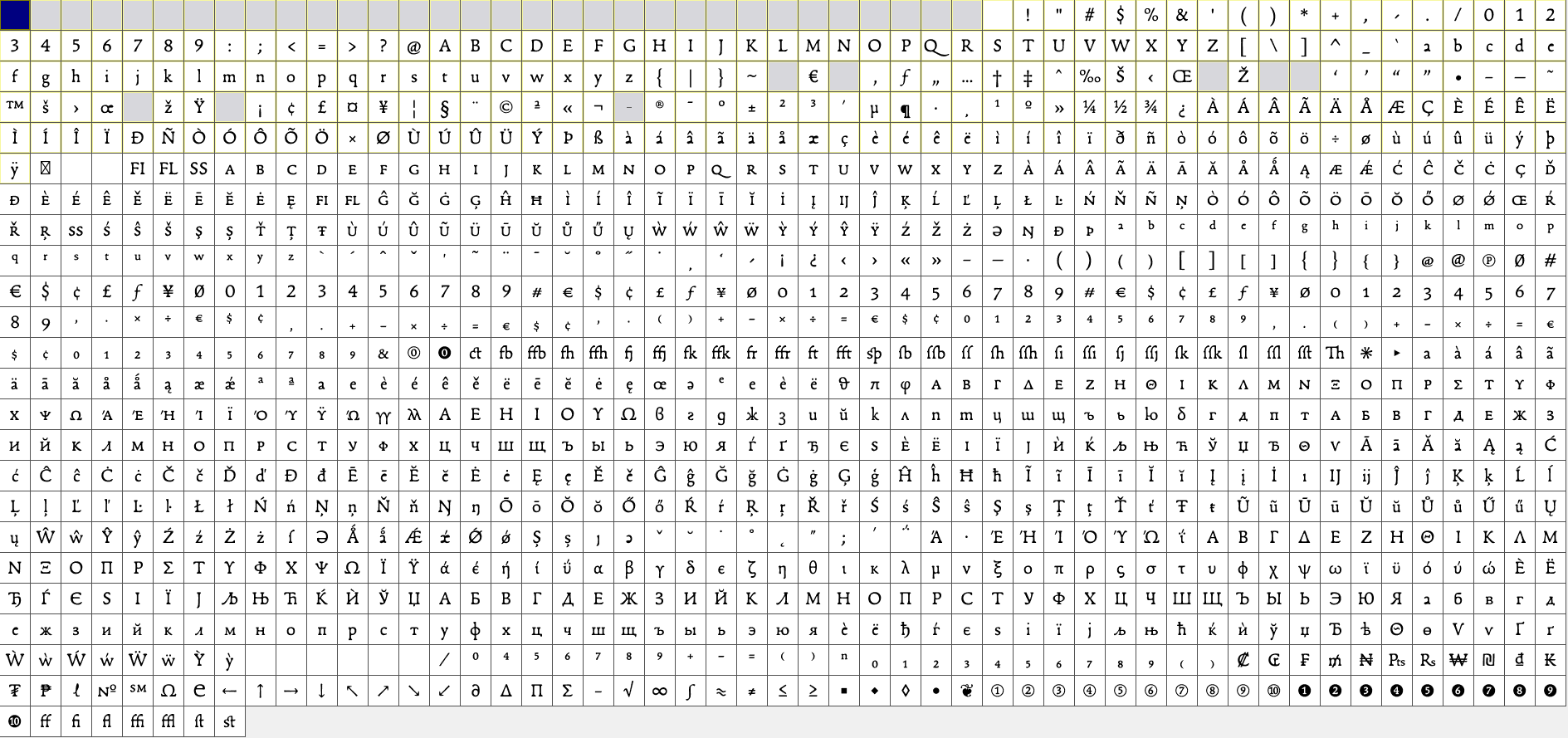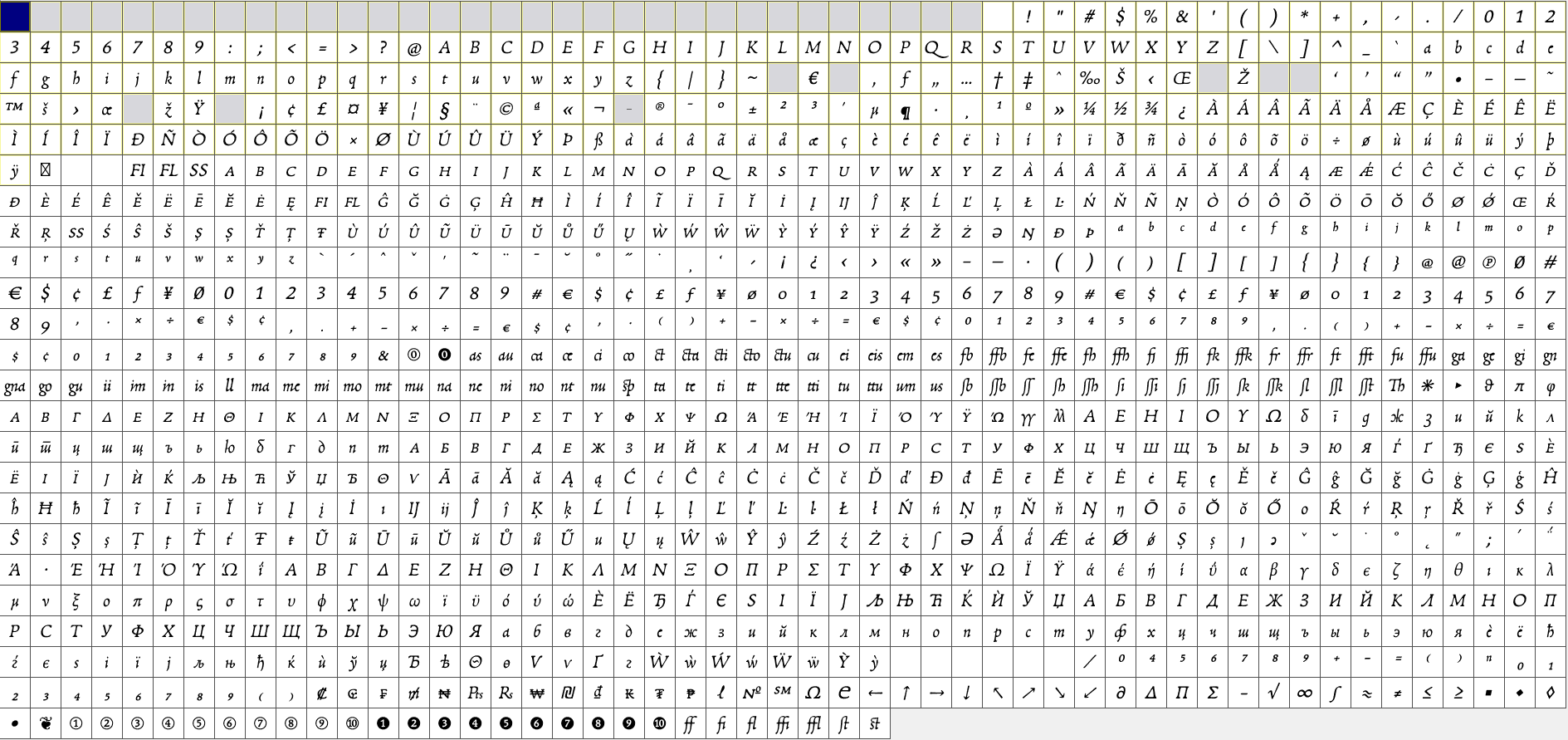
Kyrillische Kapitälchen
Hä? Wie bitte sehen kyrillische Kapitälchen im Gegensatz zu kyrillischen Kleinbuchstaben aus???
Wie im Lateinischen so sind sich auch im Kyrillischen nicht alle Majuskeln und Minuskeln ähnlich. Daher bleibt auch im Kyrillischen Platz für Kapitälchen (also Versalformen, die annähernd x-hoch sind). Ich habe mal meine Schriften nach kyrillischen Kapitälchen gescannt und bin selbst erstaunt, in wievielen Fonts diese enthalten sind:
PF Adamant Pro
Adobe Text
Arno Pro
Baltica
Bonesana Pro Expert
Calibri
Cambria
Candara
PF Centro Serif Pro
Constantia
Corbel
Fedra Serif B
Francesco
HS Garamond Pro
Original Garamond BT
Garamond Premier Pro
Georgia Pro
Graublau Sans
Hypatia
Kis BT
Künstler 480 BT
Ladoga
Leksa
Oktava
Really No. 2 LT W1G
Scotch Modern
Venetian 301 BT
Ich hoffe, alle Schriftnamen den richtigen Bildern zugeordnet zu haben. Wer weiterführende Informationen zu den Schriften benötigt, soll es bitte sagen. (Ich war zu faul, jetzt jede Schrift zu verlinken.) Wer weitere Buchstaben sehen möchte, sage es ebenfalls. Dann werde ich entsprechend nachliefern.
Ganz vielen Dank für die schöne Übersicht. Magst du mir ein paar Infos zur Franceso geben? Die sieht interessant aus :)
Die Francesco stammt aus der Feder von Franck Jalleau und wurde vom französischen Bureau des Affaires Typographiques herausgegeben.
Für das geschlossenen a und e gibt es offenere Alternativen:
Die Francesco schreibt Lateinisch, Griechisch und Kyrillisch. Sie umfasst jedoch nur einen aufrechten und einen kursiven Schnitt. Beide beinhalten Kapitälchen und zahlreiche Zifferformen.
Auch dafür vielen Dank! Leider ist mal wieder nur das halbe Griechisch* dabei :(
* Ich werde nie verstehen, warum jemand, der sich die Mühe macht, Griechisch zu zeichnen, nicht einfach noch die ein, zwei Akzente für Greek Extended mitzeichnet (die erst 1982 abgeschaft wurden)... :(
Ich werde nie verstehen, warum jemand, der sich die Mühe macht, Griechisch zu zeichnen, nicht einfach noch die ein, zwei Akzente für Greek Extended mitzeichnet
Weil es ein beträchtlicher Aufwand ist, den Polytonisch-Block 1F00 komplett durchzuarbeiten: ca. 240 zusätzliche Zeichen, die alle erstellt und kontrolliert werden müssen.
Von wegen »zwei Akzente«.
Ergänzend dazu: es gibt immer noch ein Akzentzeichen mehr, dass für sich genommen schnell zu machen ist. Selbst im lateinischen Bereich nimmt das theoretisch kein Ende. Und in den anderen Schriftsystemen (kyrillisch, griechisch etc.) sieht es ganz genauso aus. Es gibt immer noch ein Akzentzeichen mehr, dass irgendjemand für irgendetwas gerne hätte.
Daher beschränkt man sich z.B. bei Schriften, die ohnehin eher auf den lateinischen Bereich abzielen, dann z.B. auf einen standardisierten Basic-Satz in den anderen Systemen. Sonst kann man bis zum Sankt Nimmerleinstag weiterbauten. Für Spezialanwendungen gibt es ja ohnehin Spezialfonts.
Weil es ein beträchtlicher Aufwand ist, den Polytonisch-Block 1F00 komplett durchzuarbeiten: ca. 240 zusätzliche Zeichen, die alle erstellt und kontrolliert werden müssen.
Von wegen »zwei Akzente«.
Wo siehst du denn da 240 Zeichen? Ich sehe da jede Menge Buchstaben, die bereits vorhanden sind und nur noch mit den diakritischen Zeichen versehen werden müssen. Und das muss noch nicht einmal precombined sein. Denn es reichte ja auch, nur die verschiedenen Akzente für das Combining zu zeichnen oder per c&p zur Verfügung zu stellen (Tilde und Gravis und Akut sind ja schon gezeichnet für Latin).
Ergänzend dazu: es gibt immer noch ein Akzentzeichen mehr, dass für sich genommen schnell zu machen ist. Selbst im lateinischen Bereich nimmt das theoretisch kein Ende. Und in den anderen Schriftsystemen (kyrillisch, griechisch etc.) sieht es ganz genauso aus. Es gibt immer noch ein Akzentzeichen mehr, dass irgendjemand für irgendetwas gerne hätte.
Und warum dann nicht auch noch die paar Akzente zusammenkopieren (die Antwort habe ich bisher noch nicht erhalten), um dem Kunden (und den weiteren Käufern) die Wahl zu lassen, öh, konservativ zu schreiben?
hierzu eine verspätete anmerkung: es gibt eine neue schrift für polytonisches griechisch, die fs olivia (vielleicht kennst du sie schon). als ich mir das schriftmuster-pdf anschaute, musste ich an dieses thema denken und sagte so zu mir: von »die paar akzente« kann angesichts des folgenden eigentlich keine rede sein.